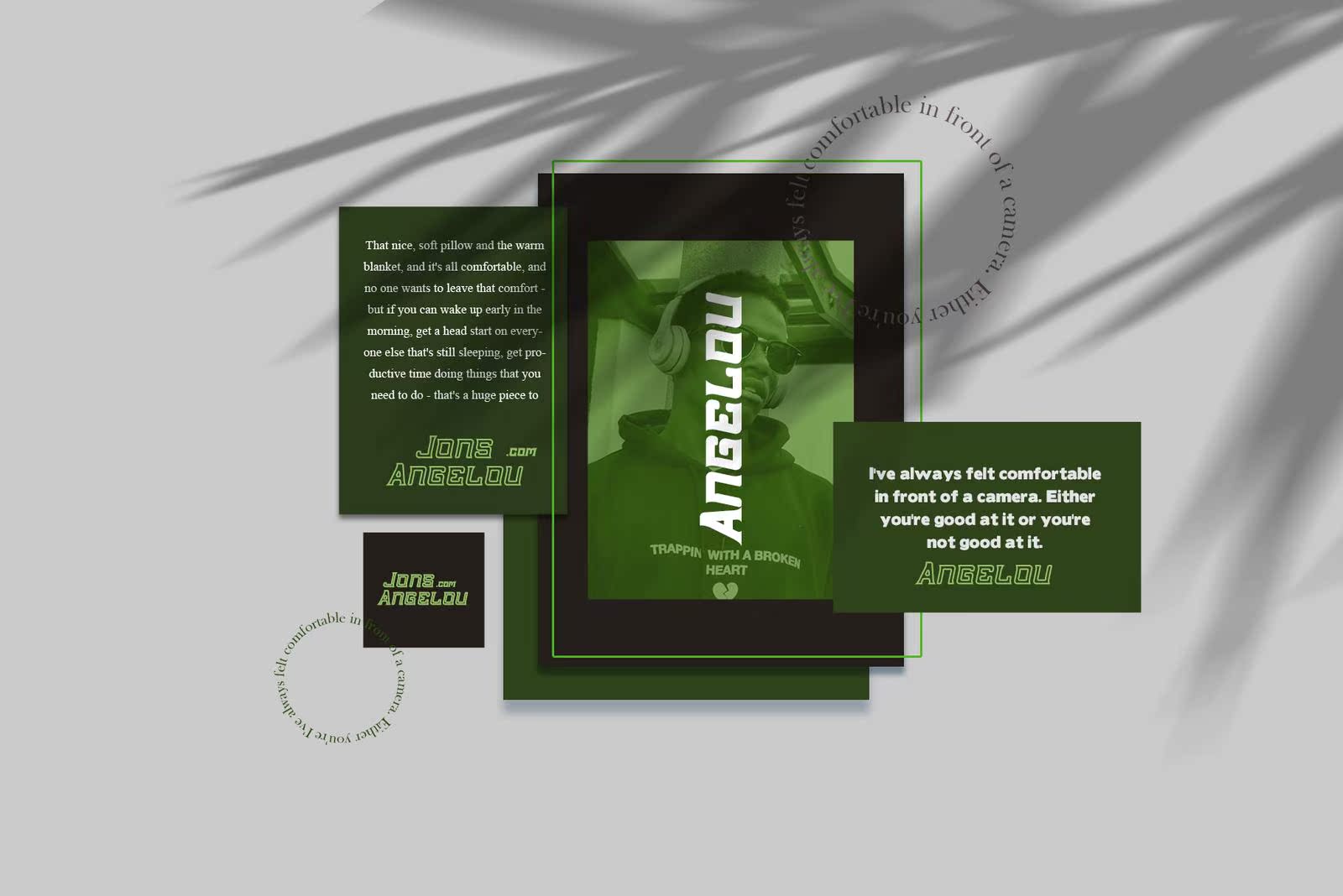
介绍新版本,BigLakeDisplay字体。此字体集适用于品牌徽标、邀请、问候卡或任何项目。具有多语言功能和样式变化,此字体将进一步增强您作品的外观。介绍新版本,BigLakeDisplay字体。此字体集适用于品牌徽标、邀请、问候卡,即使是任何类型的项目。具有多种语言功能和样式变化,这种字体将进一步增强您的工作的外观。